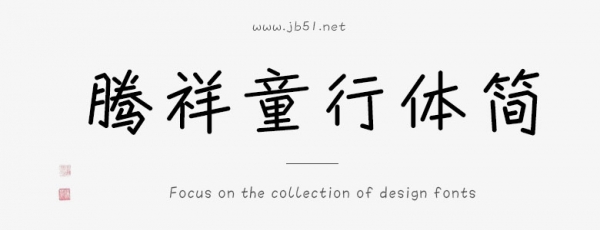
騰祥童行體簡是一款不錯的藝術(shù)字體,由騰祥字庫出品,字體筆畫舒展流暢,頓挫有秩;筆畫間相互呼應(yīng)且張弛有度,適合應(yīng)用于藝術(shù)設(shè)計、平面宣傳設(shè)計、網(wǎng)頁設(shè)計,書法字帖等領(lǐng)域,需要的朋友可以前來本站下載。
此款字為手繪美術(shù)字體。風(fēng)格鮮明、特點突出。筆畫舒展流暢,頓挫有秩;筆畫間相互呼應(yīng)且張弛有度;字面大小均勻,筆畫規(guī)范。整款字透顯出行書行筆特點,然而又打破傳統(tǒng)書法概念運用新的手寫方法形成一款生機盎然、清新活潑的字體,本款字在不影響閱讀的前提下盡顯其特性。本作品可適用于印刷排版兒童讀物、包裝設(shè)計、廣告設(shè)計、網(wǎng)頁設(shè)計、屏幕顯示等媒體。